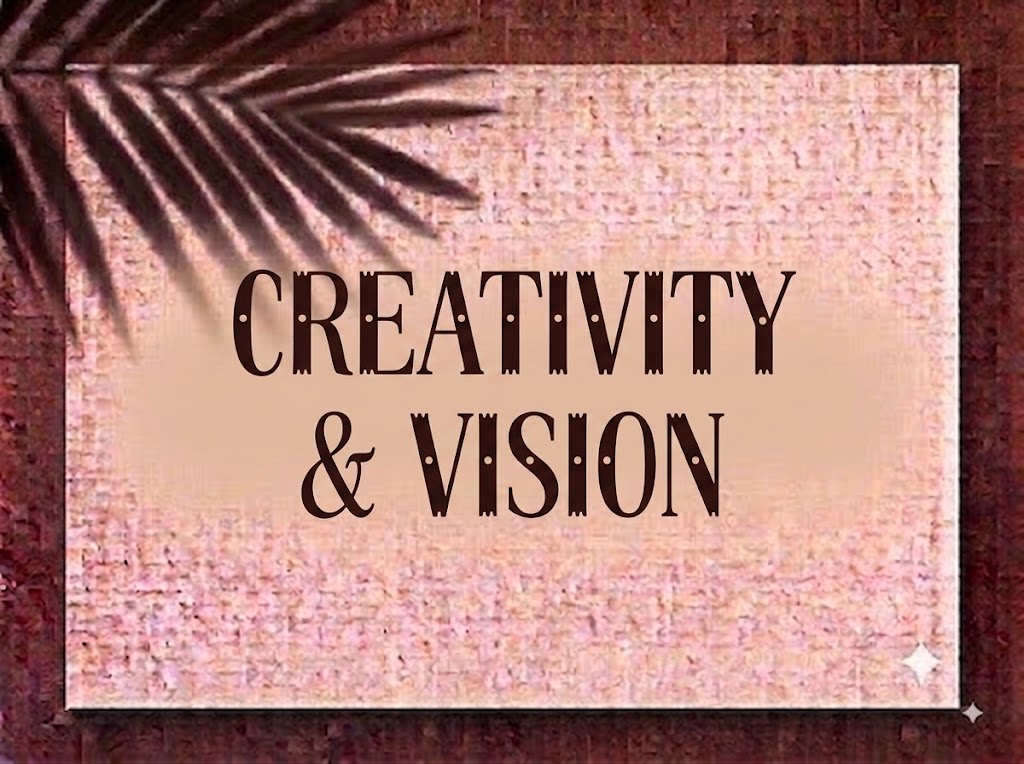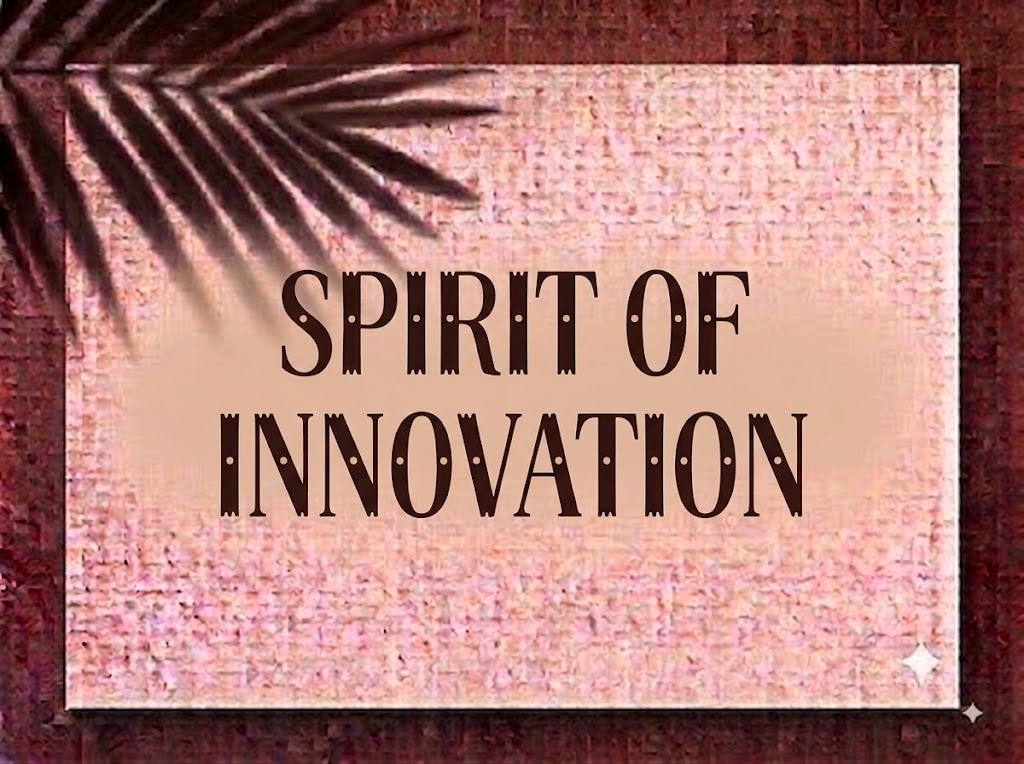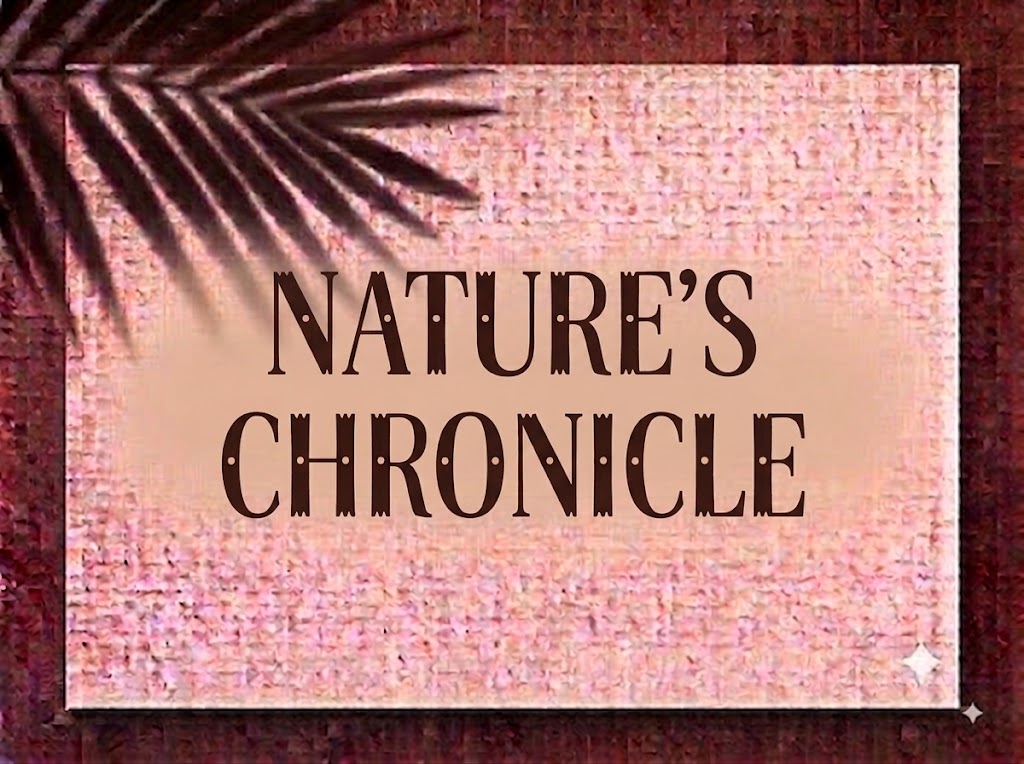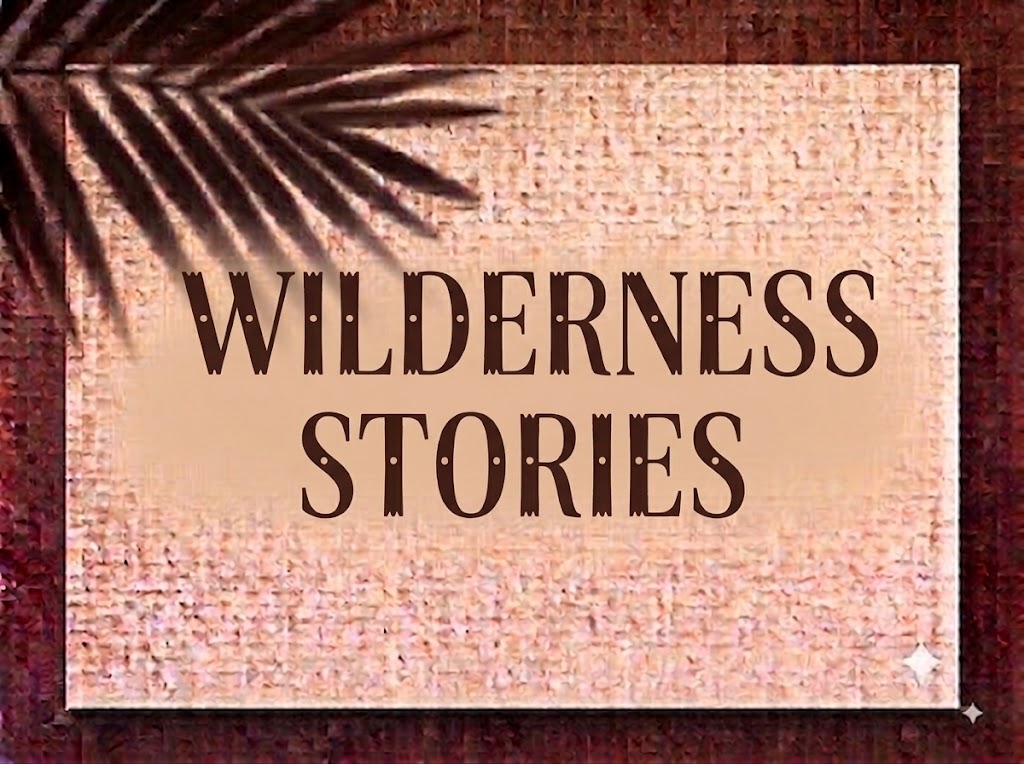
1FTV Dacquoise
Trong nghệ thuật thiết kế truyền thông và sáng tạo nội dung hình ảnh, những bộ phông chữ trang trí (decorative display font) sở hữu họa tiết bề mặt và đường nét phá cách luôn là công cụ hiệu quả để tạo ấn tượng thị giác kịch tính. Một dòng tiêu đề được đính kèm các hiệu ứng khắc vạch, nét xoắn gợn sóng và điểm chấm trang trí không chỉ giúp thông điệp trở nên sinh động mà còn mang đến không khí lễ hội, hoài cổ đầy mê hoặc.
Nếu bạn đang tìm kiếm một phông chữ hiển thị mang phong cách rạp xiếc (circus), carnival cổ điển hay bánh ngọt/gỗ khắc thủ công để làm banner chương trình, poster sự kiện, nhãn mác sản phẩm hay tiêu đề video ngắn, font 1FTV Dacquoise chính là sự lựa chọn không thể bỏ qua.
Giới thiệu về font 1FTV Dacquoise
Font 1FTV Dacquoise là bộ chữ hiển thị trang trí mang phong cách Vintage Carnival & Handcrafted Texture, nổi bật với sự kết hợp hài hòa giữa cấu trúc chữ đứng dáng và hệ thống họa tiết bề mặt sinh động:
Tên phông chữ: 1FTV Dacquoise
Được thiết kế và hoàn thiện chỉn chu trên chuẩn OpenType, phông chữ đem lại khả năng hiển thị vô cùng mượt mà. Bạn có thể tự tin phóng lớn tiêu đề trên các phần mềm thiết kế đồ họa chuyên nghiệp hay ứng dụng dựng video mà không lo bị vỡ nét hay dính chi tiết.
Đặc điểm nổi bật của phong cách thiết kế Dacquoise
Sức hút thị giác của font 1FTV Dacquoise nằm ở cấu trúc hình khối độc đáo cùng các chi tiết tạo hình đầy tính nghệ thuật:
Họa tiết vạch sọc & chấm tròn điểm xuyết: Điểm đắt giá nhất của phông chữ nằm ở phần thân chữ được trang trí bởi các đường rãnh vạch đứng song song kết hợp cùng những chấm tròn nhỏ xinh bên trong (như ở các ký tự
Q,B,R,O,P,D,G). Chi tiết này tạo nên hiệu ứng thị giác như những biển hiệu rạp xiếc rực rỡ hay đồ gỗ khắc tay tỉ mỉ. -
Nét xoắn Curlicue cổ điển kiêu sa: Phần đầu và chân của các ký tự như
T,C,E,F,J,Sđược uốn cong nhẹ nhàng, đem lại vẻ mềm mại, duyên dáng cân bằng lại với cấu trúc nét thẳng dầy dặn. -
Định dạng All-Caps kiên cố: Hệ thống ký tự in hoa đồng bộ giúp các câu tiêu đề hay slogan luôn giữ được sự vững chãi, nổi bật và thu hút ánh nhìn ngay từ giây đầu tiên.
Khoảng cách giữa các chữ (kerning) và độ giãn dòng được tính toán chuẩn xác, giúp các đường nét sọc và chấm tròn khi đứng gần nhau không bị dính nét hay gây ngột ngạt thị giác.
Tích hợp trọn vẹn bộ chữ cái in hoa, dãy chữ số 0-9 phom dáng nhí nhảnh cùng hệ thống ký tự đặc biệt, dấu câu thông dụng.
Hình ảnh demo thực tế của font 1FTV Dacquoise
Khả năng hiển thị của phông chữ này được tối ưu rất tốt trên nhiều tỷ lệ kích thước khác nhau:
Kích thước nhỏ (12pt – 24pt): Cấu trúc nét rành mạch giúp các khối chữ và dãy số vẫn hiển thị rõ ràng trên các giao diện màn hình di động.
Kích thước lớn (36pt – 72pt): Đây là đất diễn lý tưởng nhất để 1FTV Dacquoise phô diễn toàn bộ sự nhộn nhịp, độc đáo của họa tiết vạch sọc và nét uốn trang trí, tạo tác động thị giác mạnh mẽ cho các dòng headline chính.
Ứng dụng trong thiết kế đồ họa và làm video
Sở hữu nét cá tính tươi vui và giàu tinh thần lễ hội, font 1FTV Dacquoise mở ra không gian ứng dụng phong phú:
Video ngắn (TikTok, Reels, Shorts): Dáng chữ trang trí bắt mắt này hiển thị rất đẹp trên khung hình đứng tỷ lệ 9:16. Cực kỳ ăn nhập với các video vlog du lịch, ẩm thực, tiệc tùng lễ hội, hướng dẫn làm bánh, đồ handmade hay clip phong cách retro.
Banner Flash Sale & E-commerce: Lựa chọn hàng đầu để giật tít các chiến dịch khuyến mãi mùa lễ, sự kiện “Carnival Sale”, “Children’s Day”, “Year-End Party” trên Shopee, Lazada, TikTok Shop hay Facebook Banner.
Thiết kế Tiệm bánh, Café & Bao bì sản phẩm: Hoàn hảo cho các nhãn mác tiệm bánh ngọt (đặc biệt là bánh Dacquoise, Macaron), menu quán café vintage, hộp quà tặng, thiệp mời tiệc sinh nhật hay poster hội chợ.
Ảnh thu nhỏ YouTube (Thumbnail): Vũ khí tuyệt vời cho các kênh làm nội dung về trải nghiệm, giải trí, vlog đời sống hay ẩm thực nhờ giao diện tươi vui và dễ gây chú ý.